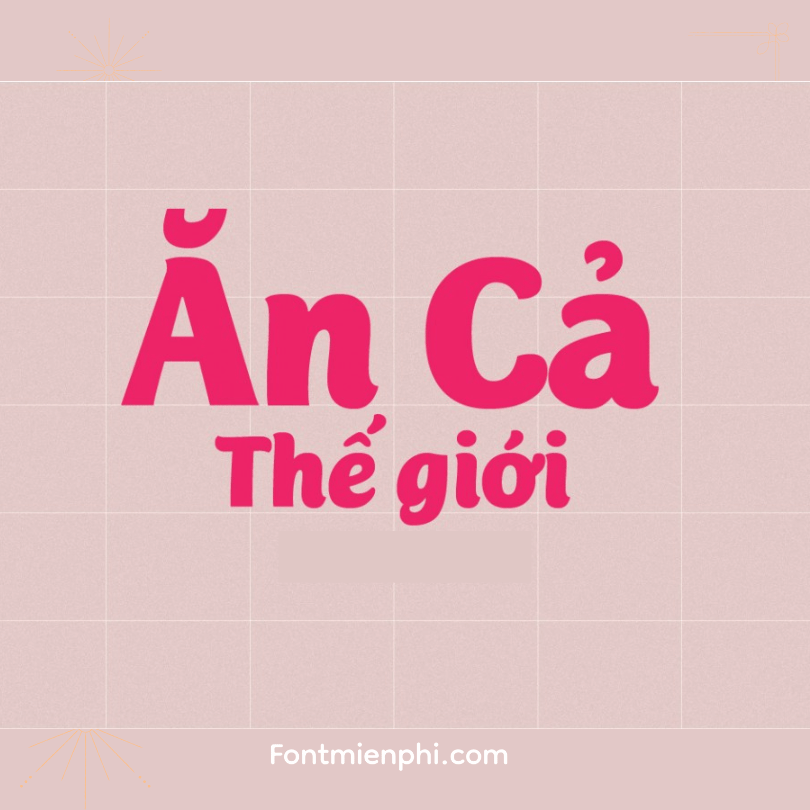
Việt hóa font iCiel Mijas , Ultra
• Tác giả:  Không rõ
• Việt hóa:  iCiel
Hướng Dẫn Việt Hóa Font iCiel Mijas Ultra
iCiel Mijas Ultra là font chữ display nét thanh mảnh, sang trọng, thường dùng cho thiết kế thời trang, tạp chí và nhận diện thương hiệu cao cấp. Dưới đây là cách việt hóa font này để hỗ trợ tiếng Việt:
1. Kiểm Tra Khả Năng Hỗ Trợ Tiếng Việt